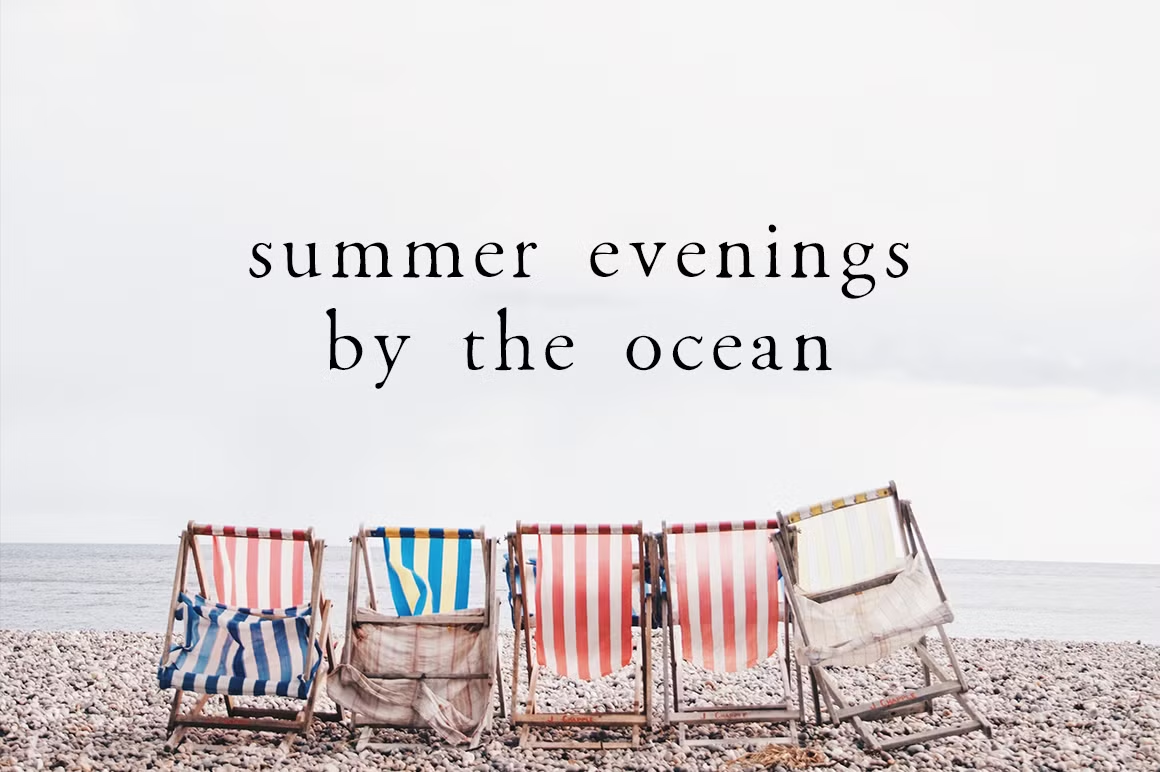
Fabello Font
Description de Fabello Font
Fabello est une police serif manuscrite de Britt Fabello. La conception est assez simple ; les lignes droites dominent la composition et l’impression générale est traditionnelle, mais si vous regardez attentivement les lettres, elles ont une courbe. Cette combinaison de designs plus audacieux et de motifs organiques plus détaillés rend Fabello tout à fait approprié. Quel que soit le design spécifique que vous avez en tête pour votre projet ou si vous souhaitez faire une déclaration audacieuse ou plus subtile, Fabello est polyvalent et peut être installé de nombreuses façons différentes.
Fabello a un design rétro avec une forme de monture d’inspiration vintage, mais le design des lunettes de soleil est toujours contemporain. Cette dualité du design le rend idéal pour les projets qui cherchent à avoir un look vintage avec une touche de monde moderne. La police est audacieuse, ce qui la rend parfaite pour les titres et les logos, tandis que les autres styles de police conviennent pour ajouter de l’élégance aux invitations, aux affiches et aux supports de marque. La vague organique à l’intérieur des lettres donne également aux lettres une apparence artisanale pour transmettre l’idée que Fabello est accessible.
Utilisation de la police Fabello
C’est peut-être l’une des polices les plus audacieuses et elle est idéale pour une utilisation dans de grandes applications telles que l’image de marque et la publicité. Cependant, pour cette raison, il est parfait pour les designs qui ont la capacité de donner un aspect très fin, ce qui peut convenir à des designs élégants comme des designs éditoriaux et des invitations de mariage. Elle fonctionne également bien sur les supports imprimés et numériques, ce qui en fait une excellente police pour les concepteurs qui ont besoin d’une police à la fois classique et fonctionnelle à utiliser dans n’importe quel projet.
Prise en charge multilingue
Il s’agit d’une police multilingue, ce qui signifie que vous pouvez l’utiliser dans différentes langues de différents pays. Divisée en lettres majuscules et minuscules, chiffres et signes de ponctuation, la police contient également un ensemble de ligatures et d’ensembles stylistiques qui seront utiles aux concepteurs.